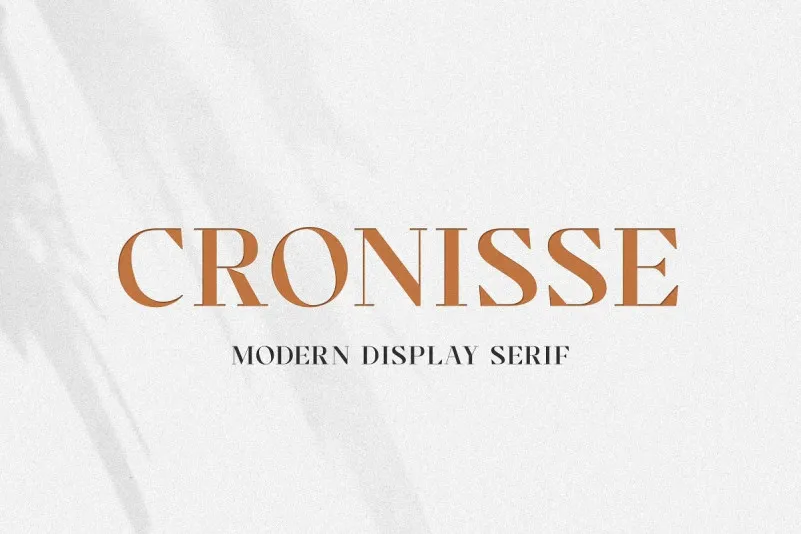
Cronisse Font
A ‘Cronisse Font’ é uma tipografia serif que traz uma atmosfera envolvente e natural à sua criação visual. Combinando formas geométricas com detalhes curvados, esta fonte mantém seu charme único inspirado na famosa logomarca minimalista, perfeitamente adaptada para os diversos objetivos de design, desde templates até logotipos e branding em grande escala. Ideal para quem busca uma combinação única entre a simplicidade de linhas retas com o movimento suave das curvas, a ‘Cronisse Font’ é um recurso gráfico que enriquece qualquer projeto. Sujeito às suas necessidades de design, ela oferece a oportunidade de criar trabalhos visuais envolventes e autênticos através da fusão perfeita entre o básico e o delicado.